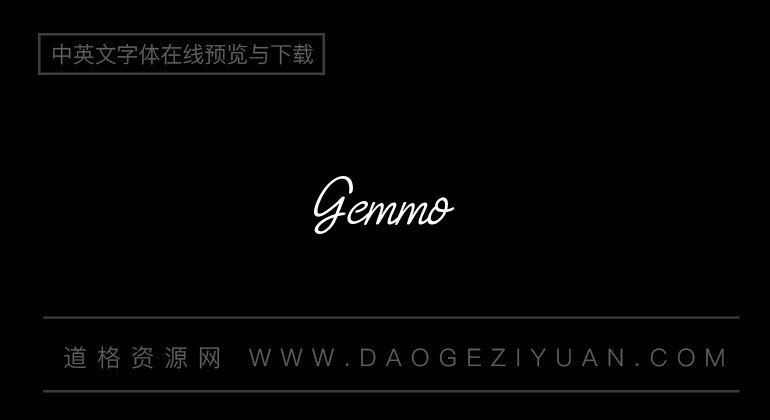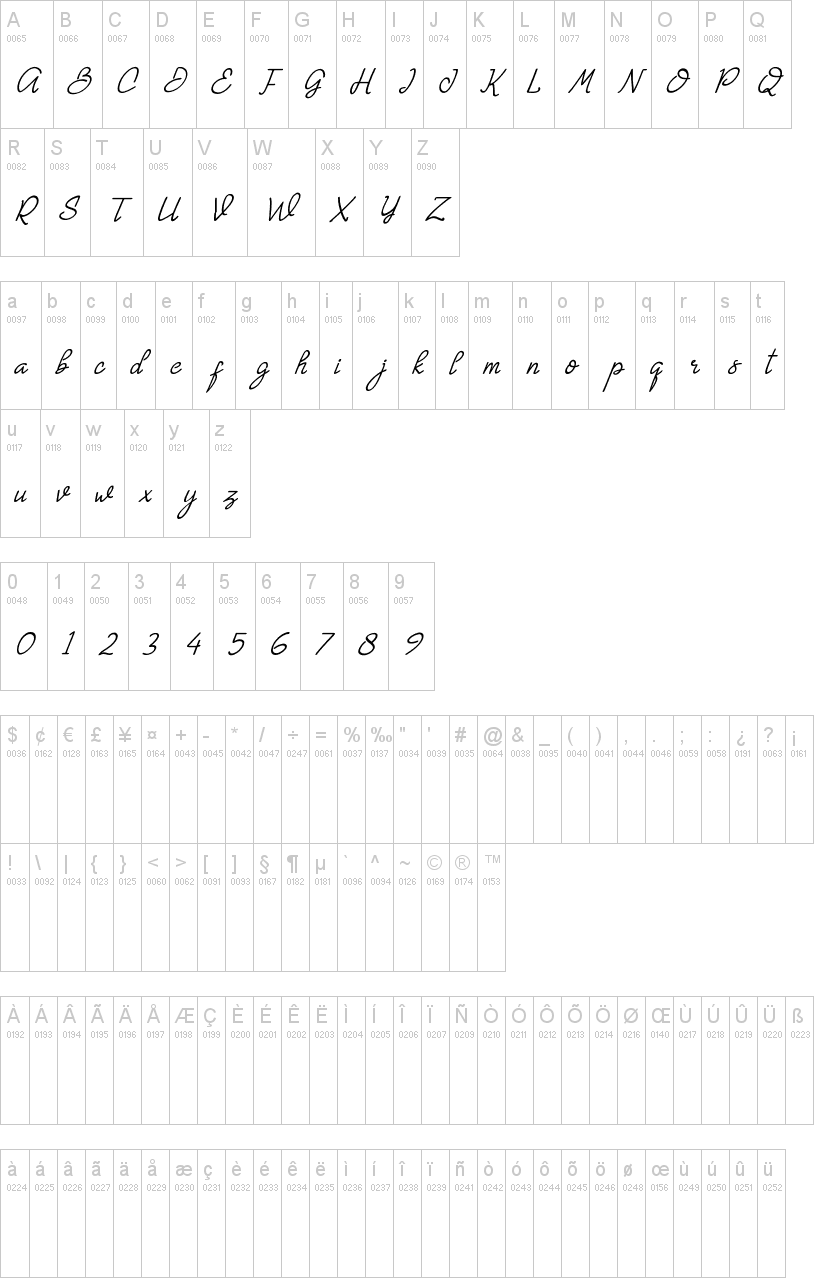
Gemmo 是一款流畅、活泼的手写字体,由 Jacob King 设计。它有两种版本:Gemmo Regular 和 Gemmo Bold。这个字体适合在许多不同的场合使用,包括印刷品、海报、包装设计、网页设计等等。 Gemmo 字体的特点是其圆润的笔画和生动的线条。它的设计灵感源于丹麦的手写风格,因此 Gemmo 字体的字母看起来非常自然、流畅。这个字体还有一些特殊的连接符号和替代字形,可以使排版更具个性化。 由于 Gemmo 字体的风格很活泼,因此它适合用于许多年轻、有活力的设计项目,比如儿童图书、音乐专辑、时尚杂志等等。它的可读性也很好,因此在设计标语、海报等需要强烈传递信息的场合也非常适合使用。内容介绍
Gemmo是一款非常不错的手写艺术字体,具有很好的视觉感,适合于文化类的宣传设计、商业类品牌的广告和产品包装设计以及个性化文字排版等较多场景。